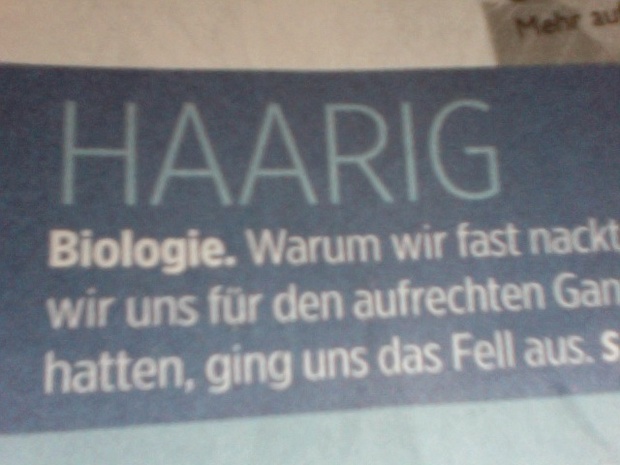
ich bekam gerade diesen schnipsle hier zugesandt und bin etwas ratlos über die verwendete schrifttype.
jemand hinweise?
Die Avenir ist von der Formensprache dicht dran aber ich glaube, dass die Proportionen nicht ganz stimmen – so weit ich das aus Deinem Beispiel ersehen kann. :-)
da auf der Abbildung der Text leider leicht verzerrt ist, kann ich den Font nicht genau vergleichen.
Aber es ist möglich, dass es die Myriad (normal und fett) ist. Es bleibt dann jedoch die Frage offen, ob das Wort „HAARIG” auch der gleiche Font ist, dann passt das mit der Myriad nämlich nicht mehr.
Vielleicht mal in dieser Richtung versuchen.
hm, Myriad ist’s eher nicht. Schau nur das a an …
Woher stammt der Schnipsel denn?